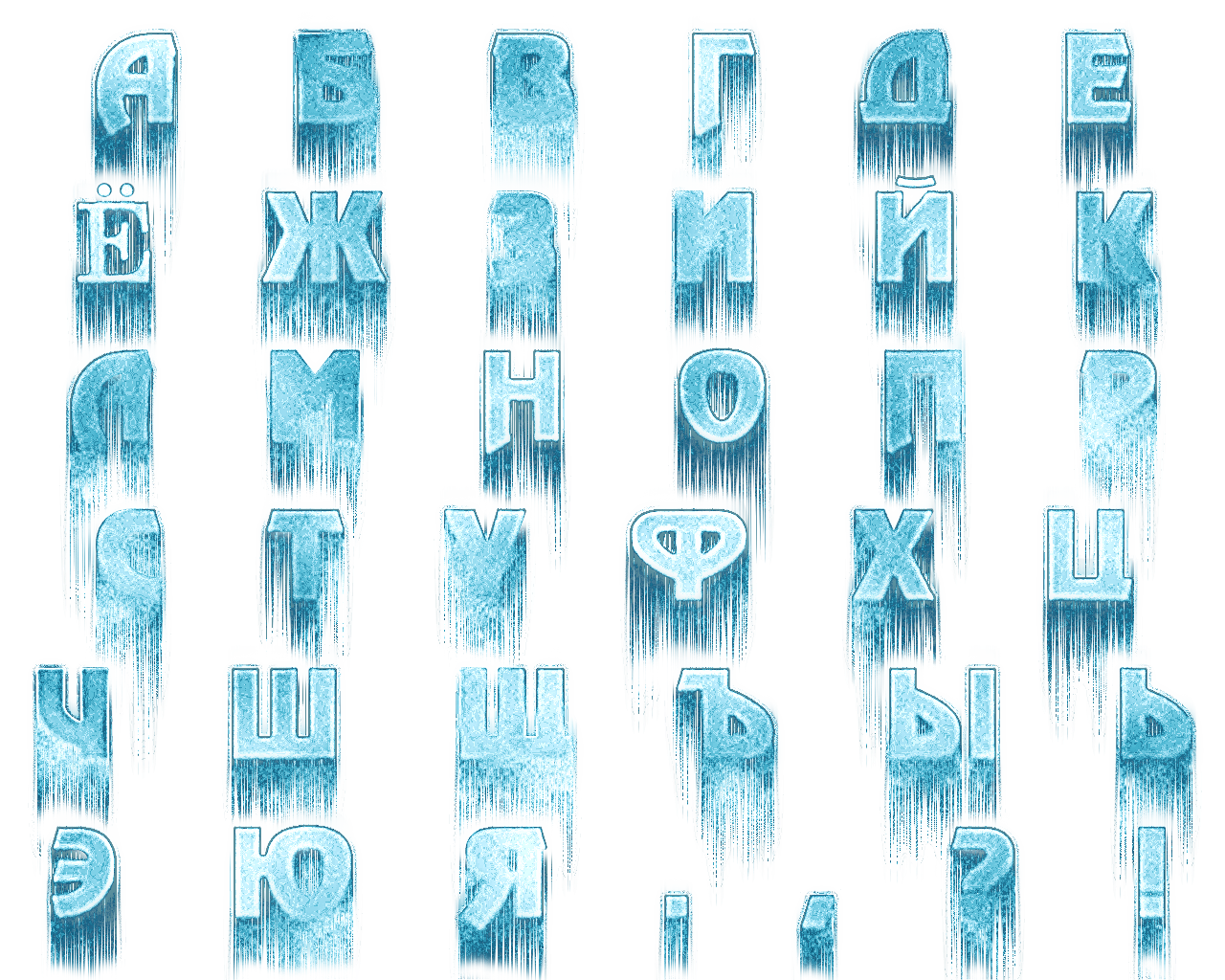
Русский зимний шрифт: Новогодние и рождественские шрифты | Шрифты онлайн
Рождественские шрифты, новогодние русские шрифты
Не смотря на то, что новый год прошел, итоги 2014 подведены я все же решил опубликовать еще одну новогоднюю тематическую заметку — про шрифты. Будет вам «заначка» материалов на следующий 2016. Однако перед тем как перейти непосредственно к новым рождественским шрифтам настоятельно рекомендую заглянуть в прошлую мою статью по этой же теме за 2010 год. Там представлено более 10-ти разных красивых вариантов, которые также будут вам весьма полезны. Плюс существует заметка с зимними шрифтами.
Повторений с теми постами никаких нет, я проверял, здесь ниже только уникальные варианты, коих по тематике рождества предостаточно. Сначала будет 20 обычных шрифтов, а потом рассмотрю новогодние шрифты русские для тех, кому нужно украшать дизайны, иллюстрации кириллицей.
PWChristmasTinsel
Весьма оригинальный рождественский шрифт, смахивающий на новогодние игрушки.
Christmas Eve
Font in a Red Suit
Frostbitten Wanker
«Снежная тематика» достаточно часто обыгрывается в новогодних шрифтах.
DJB Holly Berry Wonderland
Некоторые шрифты можно лишь косвенно причислить к рождественским. В них может и не быть ничего выдающего тематику, просто праздничные буковки. Как, например, этот и следующий.
Xiomara
Faux Snow
Порой шрифты вообще не содержат буквы, вместо них разные новогодние символы. В Faux Snow это снежинки.
Hand Christmas Doodle
Hultog Snowdrift
Опять же снежный шрифт, дальше еще парочка таких.
KB Jellybean
Вот то, о чем я уже говорил ранее. Шрифт KB Jellybean вполне мог вписаться в какую-то подборку «оригинальные простые шрифты». Лишь совмещая его с соответствующим антуражем, например, новогодними текстурами можно получить соответствующее настроение.
Snowflake Letters
One Starry Night
Красивый рукописный шрифт.
Xmas TFB Christmas
Новогодний шрифт Xmas TFB Christmas содержит только символы праздника, никаких букв.
Santas Big Secret
Dickensian Christmas
Christmas Ligtness
Само название шрифта Christmas Ligtness как бы советует добавить в нем световой эффект, после чего надпись сразу заиграет новыми красками.
Merry Xmas
Christmas Snow
Harrington
Отличный шрифт для рождественских открыток и иллюстраций.
Magic Christmas
Новогодние русские шрифты
Также я поискал парочку новогодних русских шрифтов для тех, кому нужно создавать иллюстрации или открытки с применением кириллицы. Их, к сожалению, оказалось значительно меньше обычных. На разных сервисах со шрифтами вы таких практически не найдете. Да, там есть кириллические шрифты, но чтобы новогодние… В некоторых случаях вам придется просто выбрать красивый шрифт и грамотно добавить под него изображение, фон, текстуру чтобы получить праздничный эффект.
Christmas Script C
Единственный русский новогодний шрифт, который имеет в названии слово Christmas, большая часть других просто похожи на праздничные шрифты.
Kuritza Regular
Из Kuritza Regular может получиться неплохая открытка.
Zanesennij
Традиционный новогодний шрифт со снегом с поддержкой кириллицы.
AmazObitaemOstrovCrazy
Это шрифт связывают со льдом и ледяными буквами — можете попробовать.![]()
Whirl Cyrillic Regular
Данный шрифт отображает «эффект ветра».
a_AssuanTitulStrDst Bold
Если сильно не всматриваться в буквы, то можно подумать что там снежинки…
a_CityNovaTitulStars Regular
… Хотя на самом деле там какие-то звездочки используются .
Pudelinka
Радостный яркий новогодний русский шрифт для поздравлений и открыток.
A Font with Serifs
Этот и последующий шрифты при комбинировании с новогодними текстурами и иллюстрациями могут сойти за рождественские.
CyrillicChancellor
Как видим, новогодние кириллические шрифты будут значительно послабее своих аналогов. Большая часть из них вообще не имеет особо отношения к праздникам, но все же может использоваться в работе. Тут все зависит от вашего мастерства применения цвета, фонов, текстур и т.